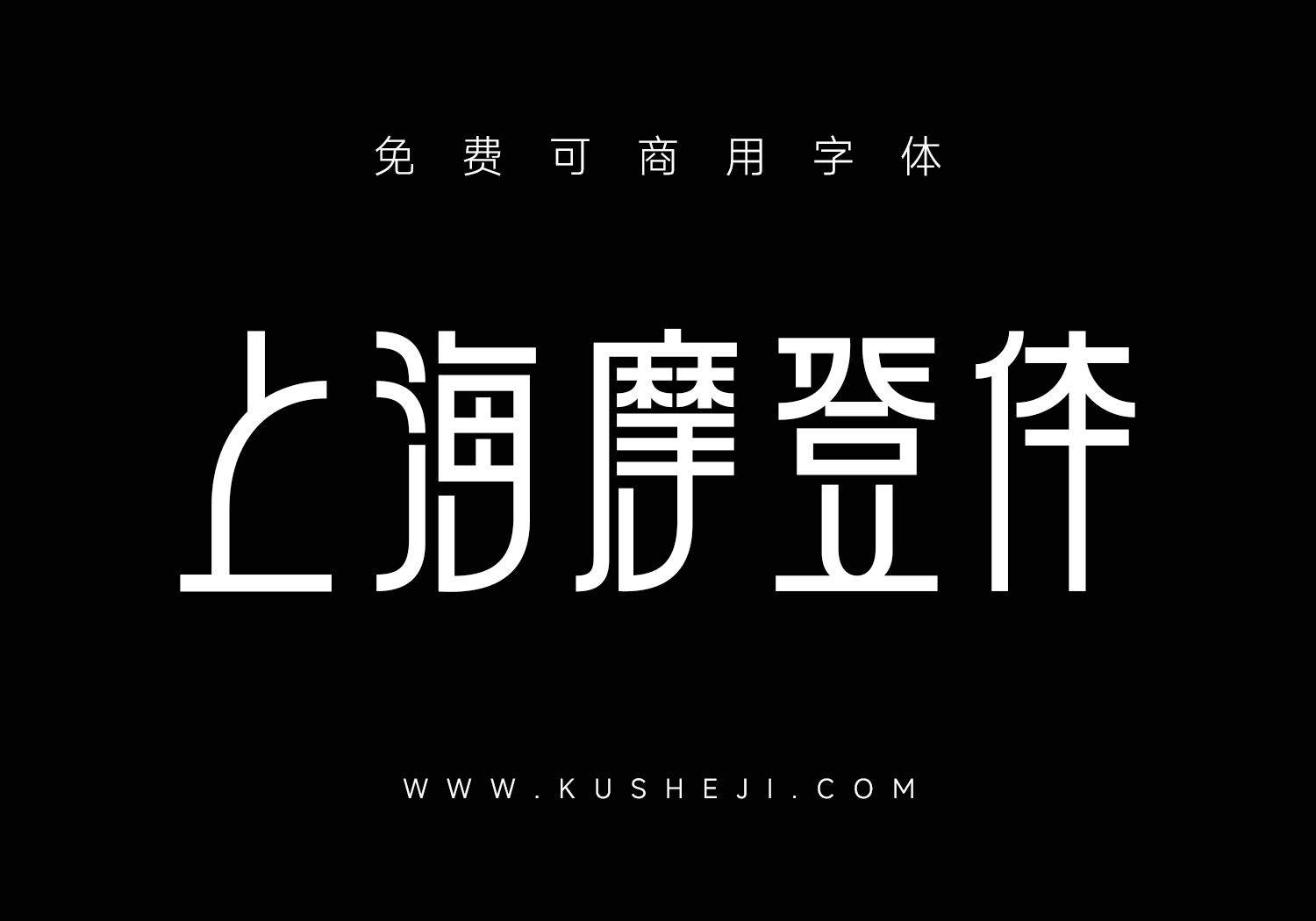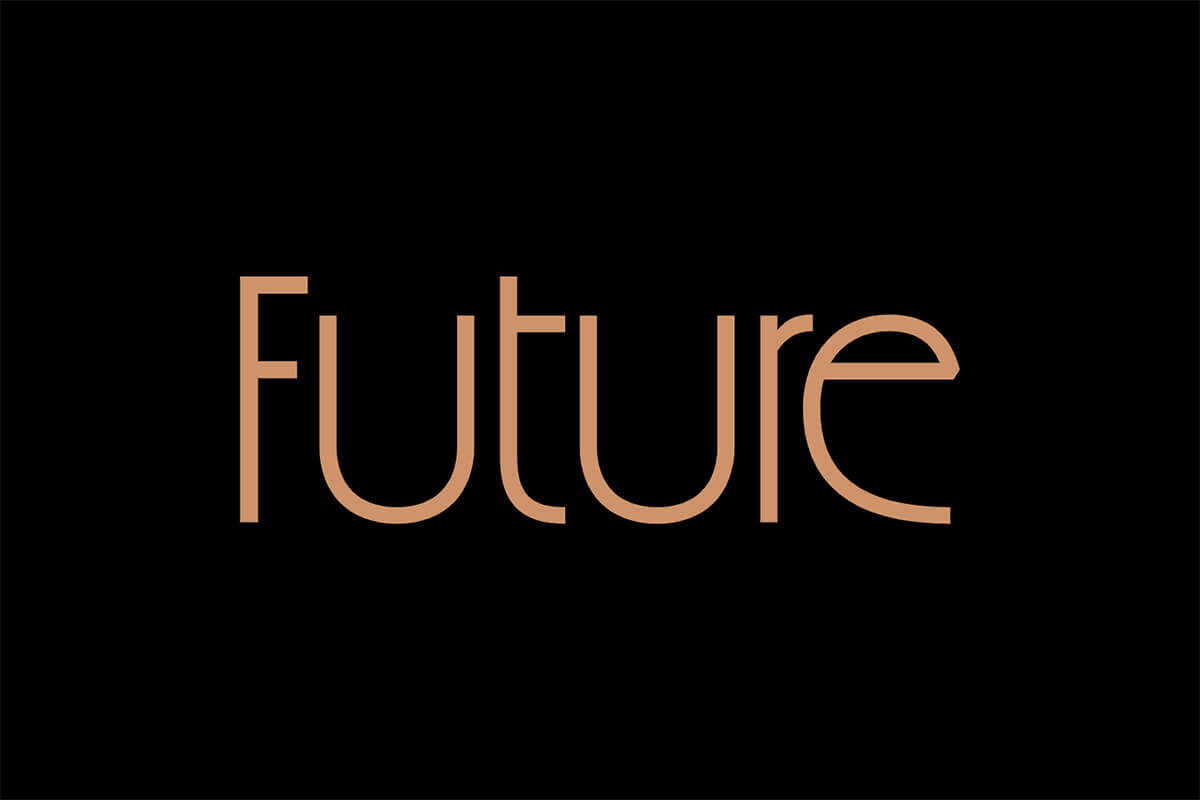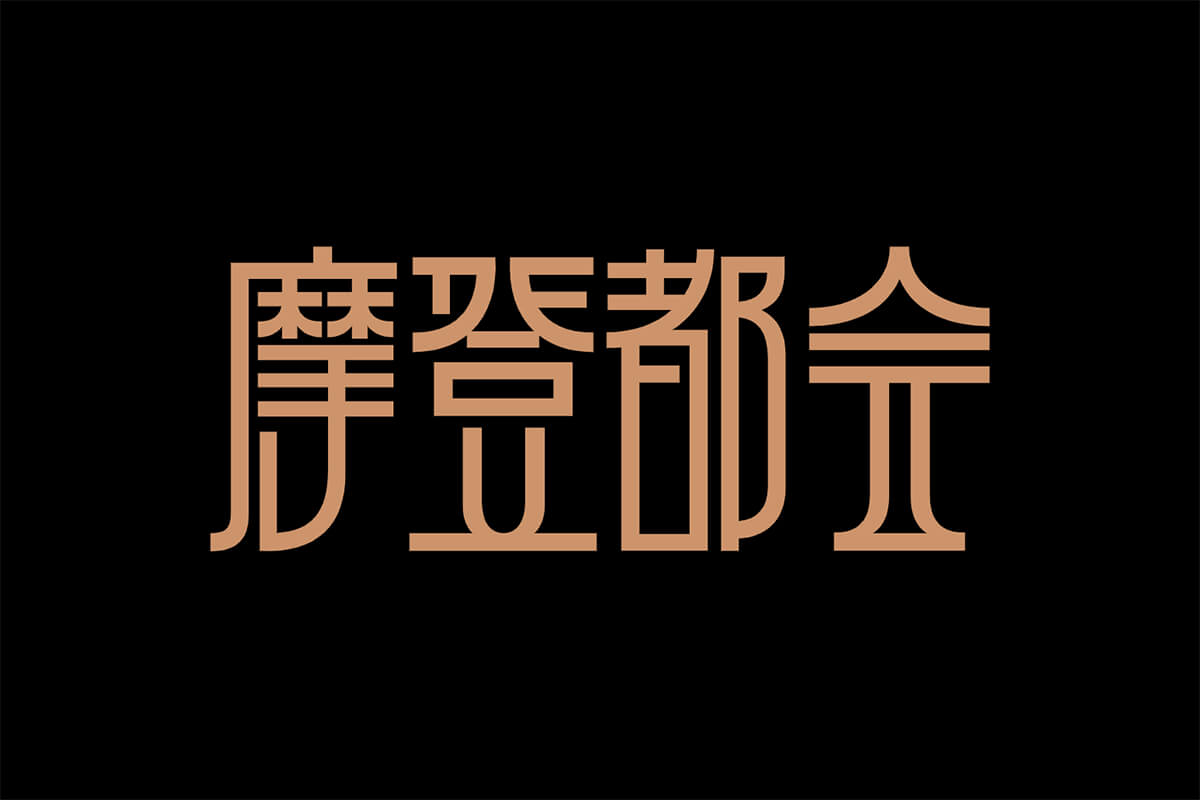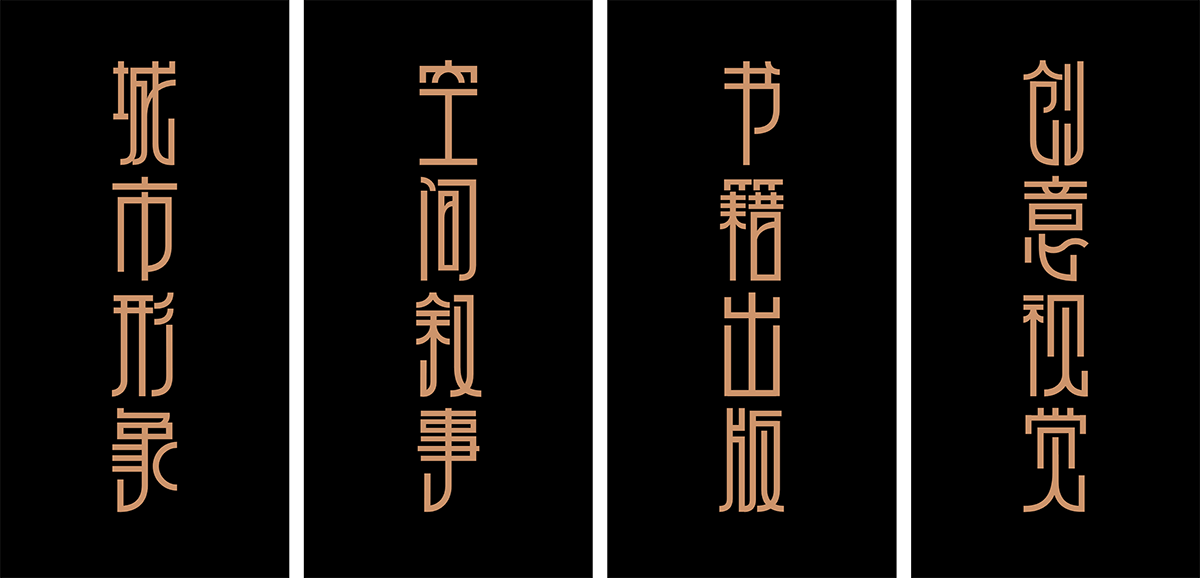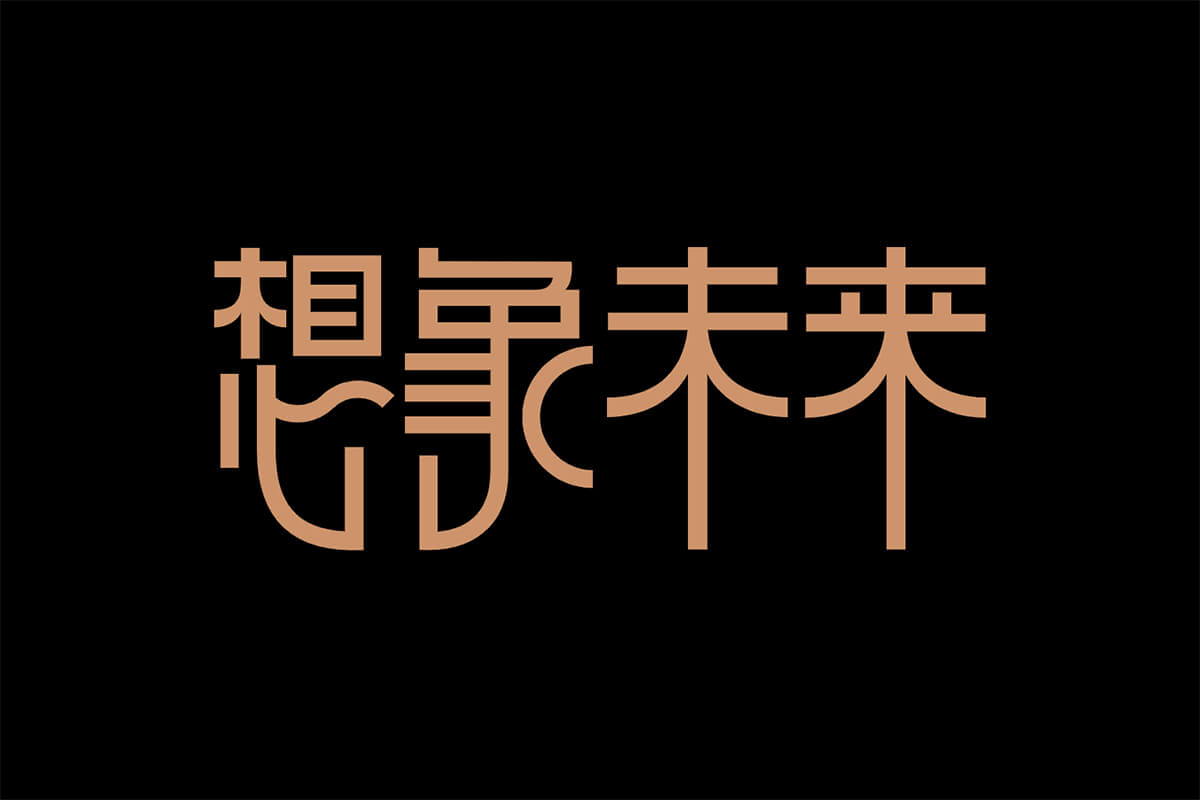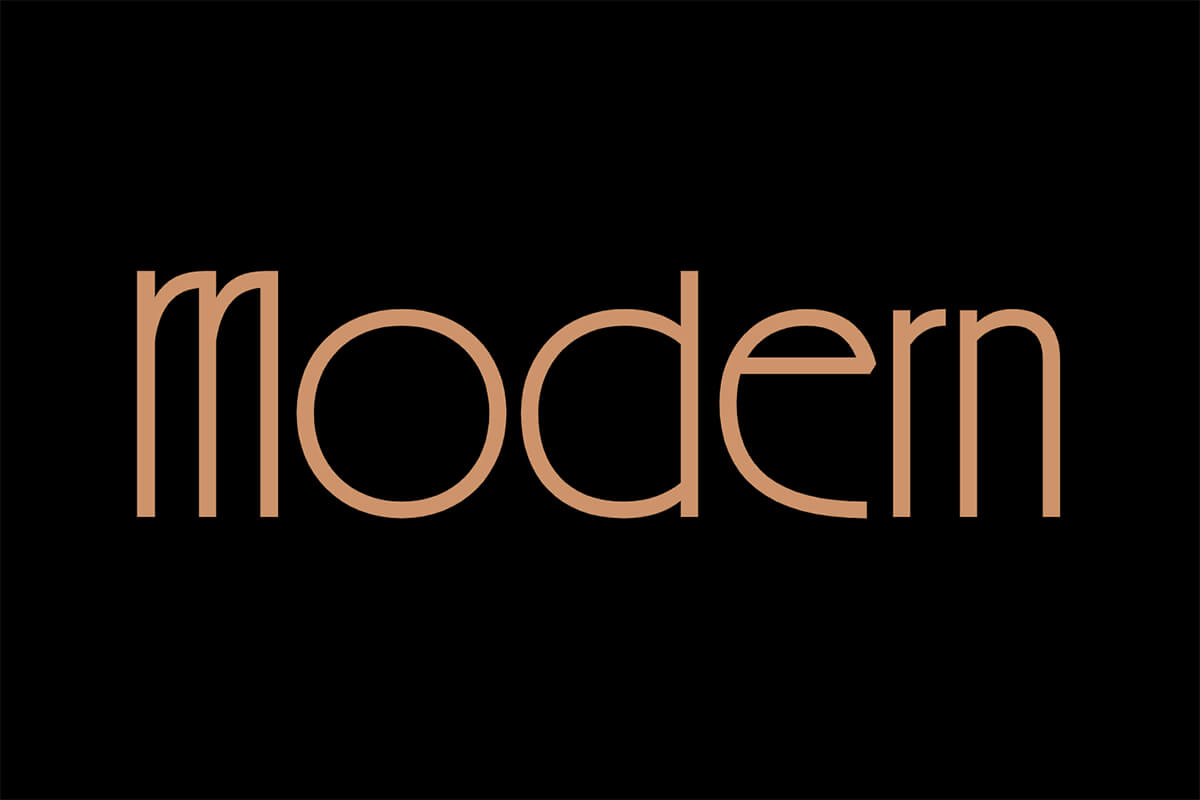
上海摩登体项目由汪汝徽联合杨林青策划;茉莉字型任字体设计;姜庆共及数位学者任学术顾问。最终呈现的字库秉承融合多元文化与创新未来的时代精神,中文以现代字库技术为基础,融入装饰艺术风格的几何美学,兼具建筑感与动态美;西文部分遵循与中文字体一致的设计理念,兼顾传统排版与现代创新;阿拉伯数字圆润饱满,从细节处强化字体的独特气质和视觉整体感。
上海摩登体(Shanghai Modeng)是中国首个以城市文化为源流的中西文字体。字库按照GB2312国标标准研发。这款字体溯源了1930至40年代伴随着上海都市文化的起源与涌现,影响与遍及了各种视觉文化形态的装饰艺术(Art Déco)运动。这款字体的设计不是对装饰艺术风格的形式复刻,而是在秉承装饰艺术运动融合多元文化与创新未来的时代精神的同时,通过独特的字形语言,向城市文明演进的过去、现在与未来的提问。